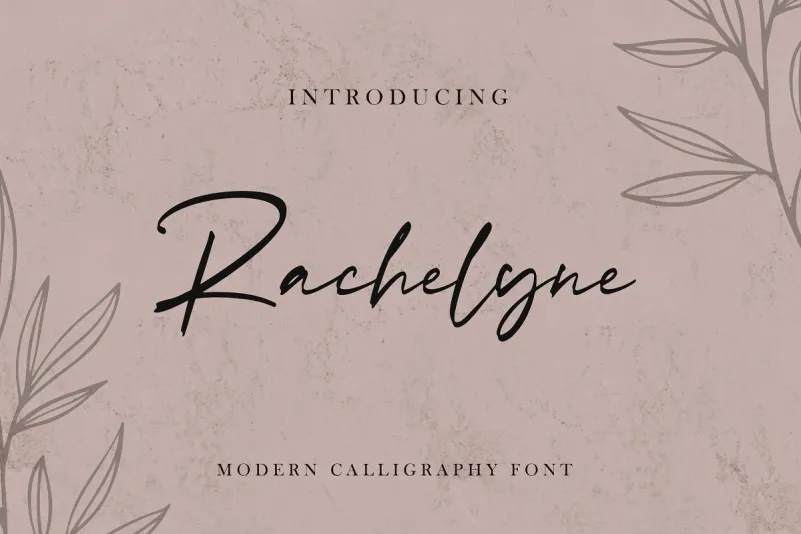
Rachelyne – Modern Calligraphy Font – Fonte Grátis
Rachelyne - Modern Calligraphy Font
A Rachelyne é uma fonte moderna criada no estilo de caligrafia manuscrita. Desenvolvida após a escrita direta, esta fonte mantém formas modernas e únicas do caligrafismo, transmitindo um estilo natural e sofisticado. Ideal tanto para marcas de moda quanto convites de casamento, cartões de negócios, logos, assinaturas e até mesmo para uso em arte gráfica tradicional, a Rachelyne é uma fonte Script Caligráfico com um toque casual. Com estilos clássico, elegante, criativo, cool e com uma ideia única, ela adiciona um toque diferenciado aos seus projetos. Com o seu design cuidadosamente pensado e desenvolvido pelo designer Hamilton, esta fonte oferece uma variedade de opções para personalizar qualquer projeto. Tornando-se a escolha perfeita não apenas para designers gráficos, mas também para quem deseja adicionar um toque de personalidade à sua própria arte ou design, seja ele em marcas de moda contemporâneas, cartões de aniversário criativos ou até mesmo em obras de arte tradicionais.